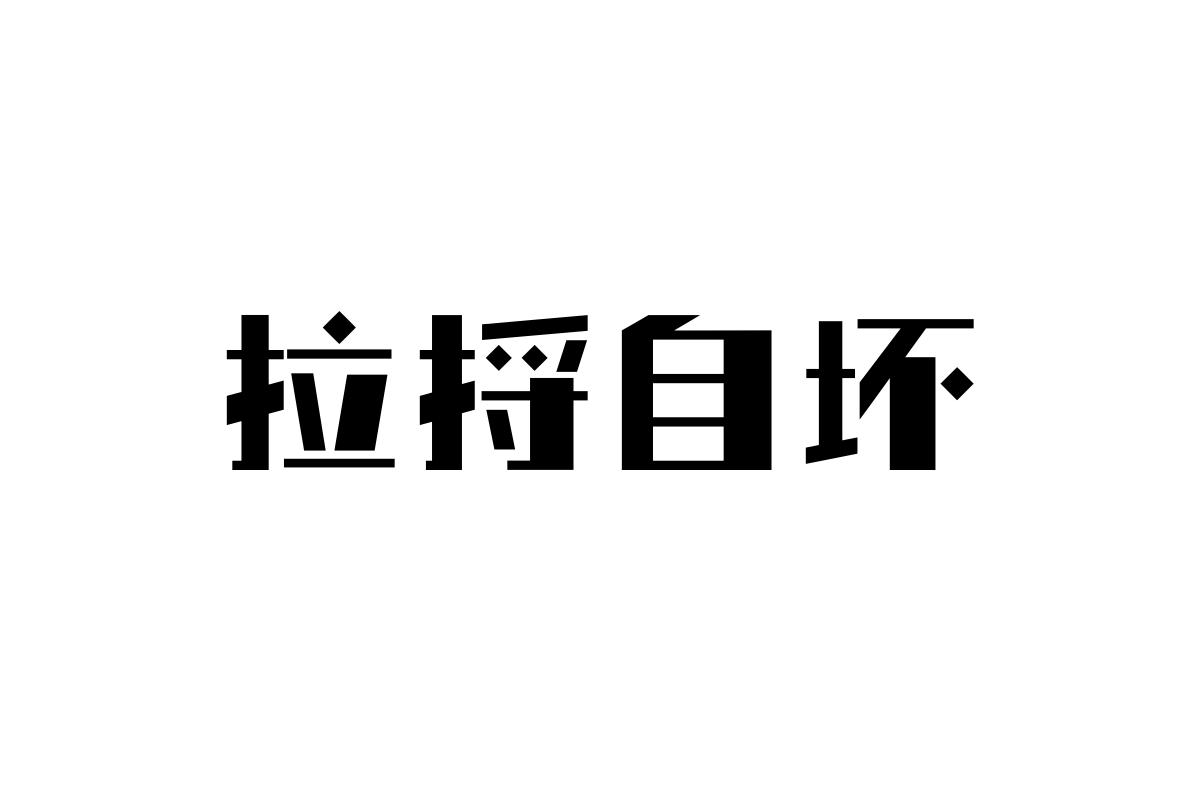
No.80-上首乐高体是一种具有特色的汉字字体,它源自于“乐高”(Lego)品牌的创意。这种字体的设计灵感来源于乐高积木的拼装过程,通过将不同的部分组合在一起,形成独特的形状和图案。
No.80-上首乐高体的字形特点如下:
1. 笔画粗细变化丰富:该字体在笔画的粗细变化上表现得非常出色,既有粗犷有力的线条,又有细腻柔和的笔触,使得整个字形更加生动有趣。
2. 结构紧凑:No.80-上首乐高体的字形结构紧凑,各个部分紧密相连,形成了一种独特的视觉效果。这使得整个字体看起来更加整齐划一,易于识别。
3. 富有趣味性:No.80-上首乐高体在设计过程中融入了乐高积木的元素,使得整个字体充满了趣味性和创意性。这使得人们在使用时能够感受到一种轻松愉快的心情,同时也增强了字体的辨识度。
4. 适用于多种场景:No.80-上首乐高体适用于各种场景,如儿童书籍、游戏、广告等。它的可爱形象和独特风格能够吸引人们的注意,提高整体的视觉效果。
总的来说,No.80-上首乐高体是一种极具创意和趣味性的汉字字体,它不仅能够提高文字的可读性和美观度,还能够为人们带来愉快的阅读体验。